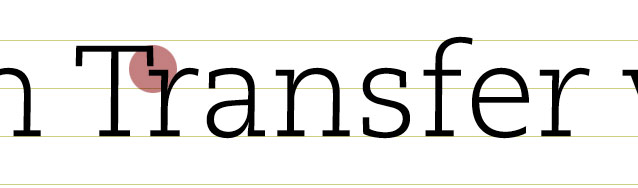
Noch eine Ligaturenfrage …
Ich setze zur Zeit ein Büchlein in der PMN Caecilia und bin gerade dabei, die falschen Ligaturen rauszufischen. Aber das f der schweren Zäzilie ist dermaßen breit, dass »f-l« ohne Ligatur so breit gesperrt werden muss wie auf dem unteren Bild, damit die Buchstaben endlich mal nicht mehr zusammenfließen. Ist das nicht zu extrem, der Abstand? Ich fürchte ein bisschen Gefahr zu laufen, dass man am Ende schon fast »beruf lich« liest.
So, what would Typoforum do? So löcherig lassen oder doch die falsche Ligatur einsetzen, zugunsten des Rhythmus?
Es ist immerhin eine Silbenfuge zwischen Stamm und Endung, wenn der umgebende Wortabstand nicht zu gering ist, kann man das Loch als das kleinere der denkbaren Übel akzeptieren.
Ich würde vielleicht versuchen, f und l doch eine Spur enger zusammenzubringen. Aber die Ligatur würde ich aus Prinzip nicht verwenden. Übrigens: Wenn schon, dann würde mich auch der etwas große Abstand zwischen b und e stören. Ach was, wenn wir schon dabei sind: Auch i und c könnten einander ein bißchen näherkommen, vielleicht auch e und r. Also was soll's, das ist eben die Schrift, lass es einfach so.
:D Dank fürs Feedback Euch beiden. Dann mach ich das mal so konsequent weiter, versuche die Lücke allerdings so schmal wie möglich zu halten.
An der Schrift (vor allem dann auch in der Fetten) sind tatsächlich einige Buchstabenpärchen ein bisschen problematisch, zum Beispiel auch das da unten. Aber ich mag sie trotzdem. Auch wenn sie mich irgendwie immer an die Thesis erinnert. :)
so eng wie möglich, aber keine Ligatur...
Sieht sicher nicht super aus, aber nicht vergessen, die Schrift ist in Lesegrößen 2-4mm hoch, bei weitem nicht alles ist da so schlimm wie man es bei 1200% Zoom sehen kann.
da gibt es wesentlich dramatischere fälle. hier die bembo:
ja, aber nicht schmaler als gezeigt. das ist ja wohl eine vergrößerte darstellung. schon so könnte es in einer lesegröße zuschmieren und aussehen wie eine hässliche buchstabenkollision.
die hätte ich an deiner stelle auch genommen, also theserif.
:D OK … I rest my case.
Ist jetzt wahrscheinlich albern und ich tu ihr unrecht damit, aber: Die Thesis kommt mir zu den Ohren raus. Wie so ein Lied, das man zu oft gehört hat. Sie ist so charakteristisch, und dieses Charakteristische sieht man so oft, dass ich sie einfach nicht auch noch einsetzen mag. Außerdem muss ich dabei immer an die Tagesschau denken.
kann ich verstehen, auch wenn die ›tagesschau‹ gerade theserif nicht verwendet. ich habe in dieser hinsicht eine höhere toleranz als andere. ich brauche mal ein paar wochen sehpause, aber dann ?nde ich auch ff din oder eben theserif wieder geil.
:hammer: Da siehste mal, wie lang ich keine deutsche Tagesschau mehr gesehen hab. Ich meinte allerdings auch weniger die TheSerif als die Thesis insgesamt. Ich schmeiß die eigentlich immer in einen einzigen großen Topf, denn für mich sehen die auch exakt gleich aus, bis auf die Serifen halt.
Och, DIN mag ich, mochte ich immer schon. Aber ich bin ja auch nicht so viel auf deutschen Autobahnen unterwegs wie wahrscheinlich andere hier. (Und sag jetzt nicht, auf den Schildern ist keine DIN … sonst wirds wirklich peinlich 8) )